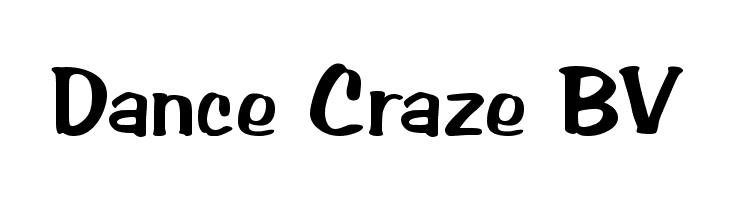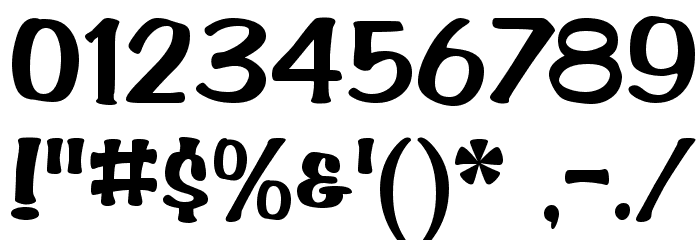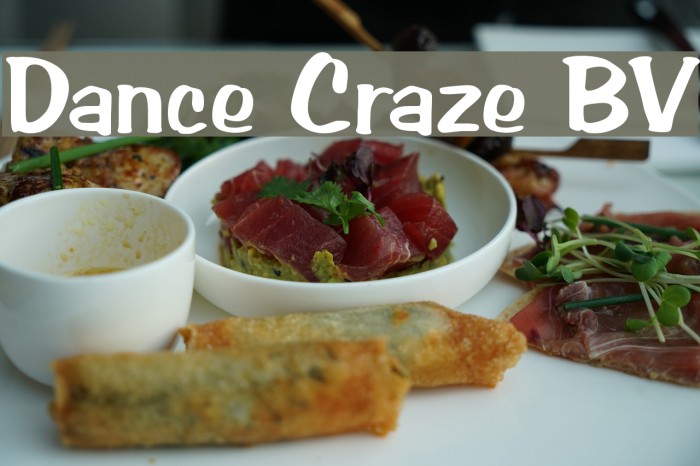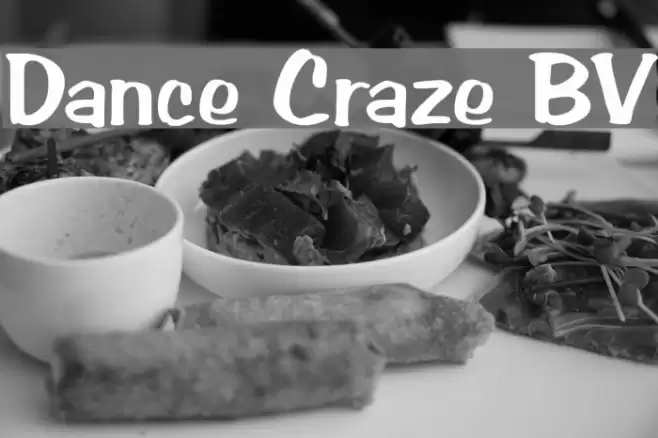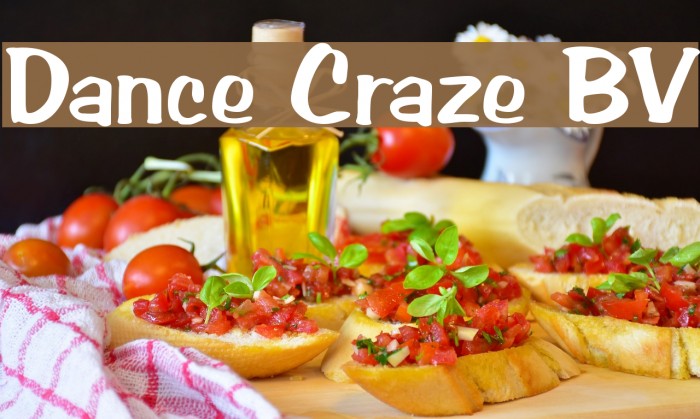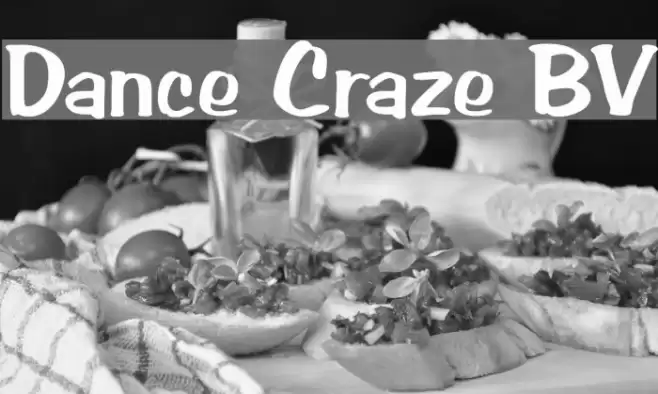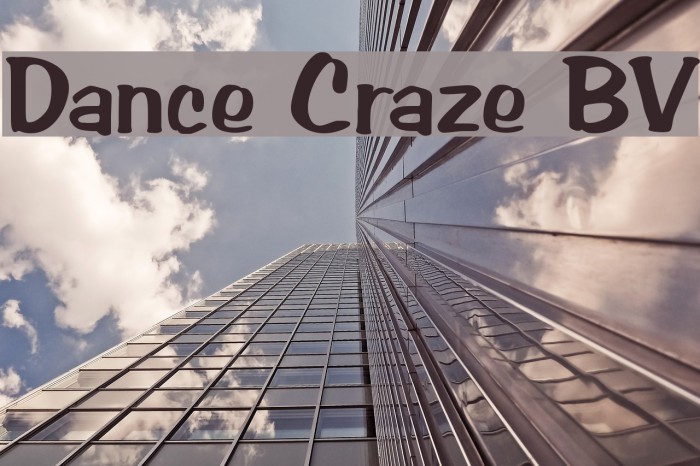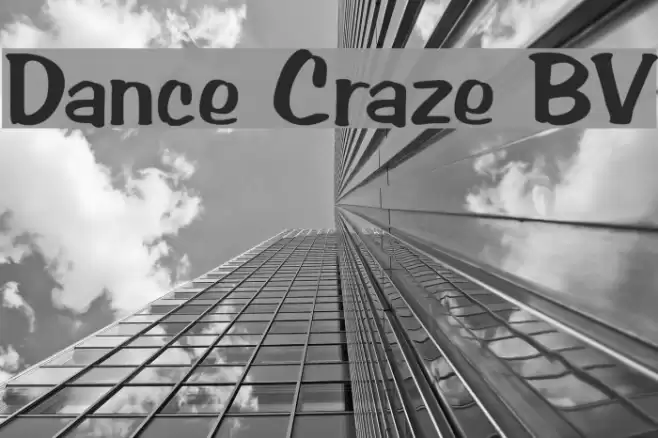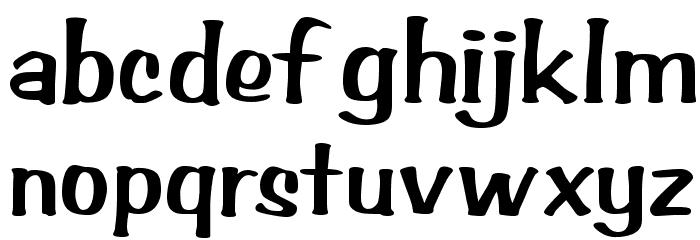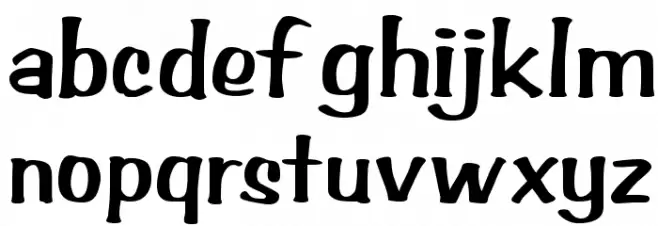
Dance Craze BV Font
| 使用场景 | Logos, Headlines, Posters |
| 推荐项目 | Perfect for children's books, playful branding, party invitations, and creative posters. |